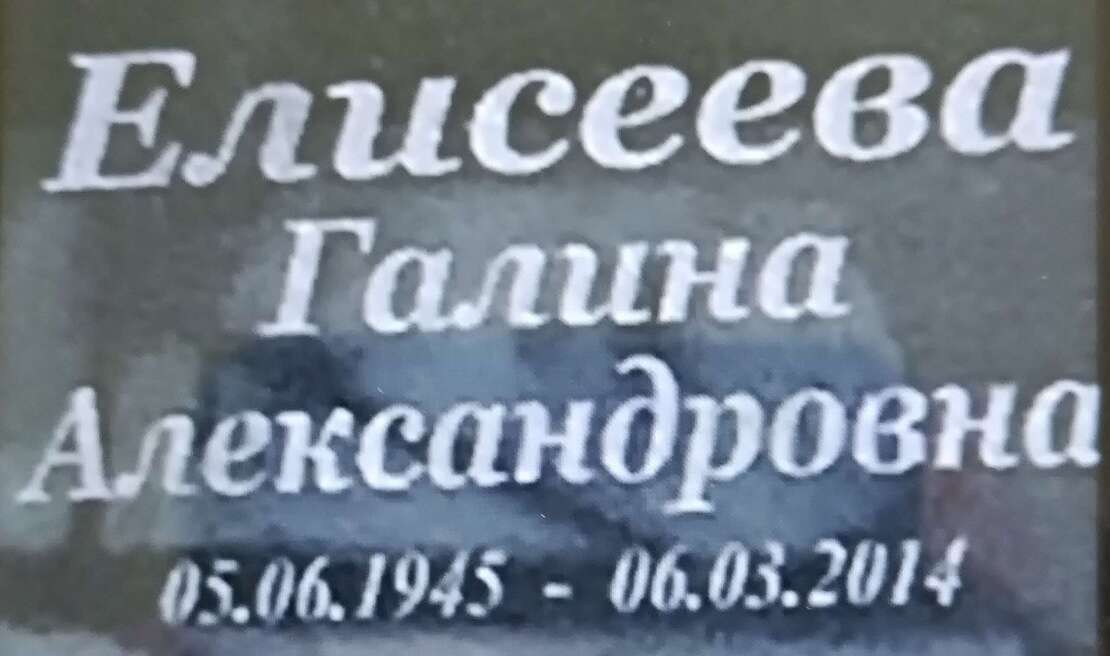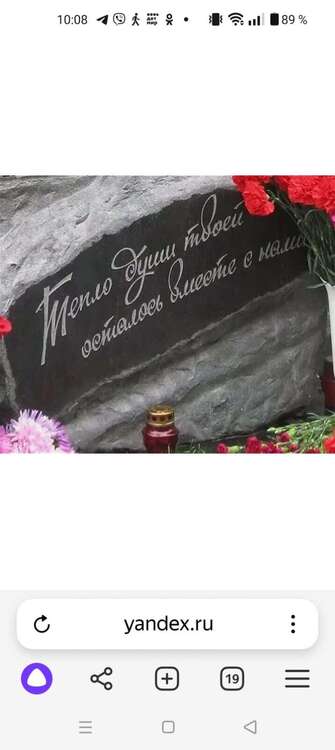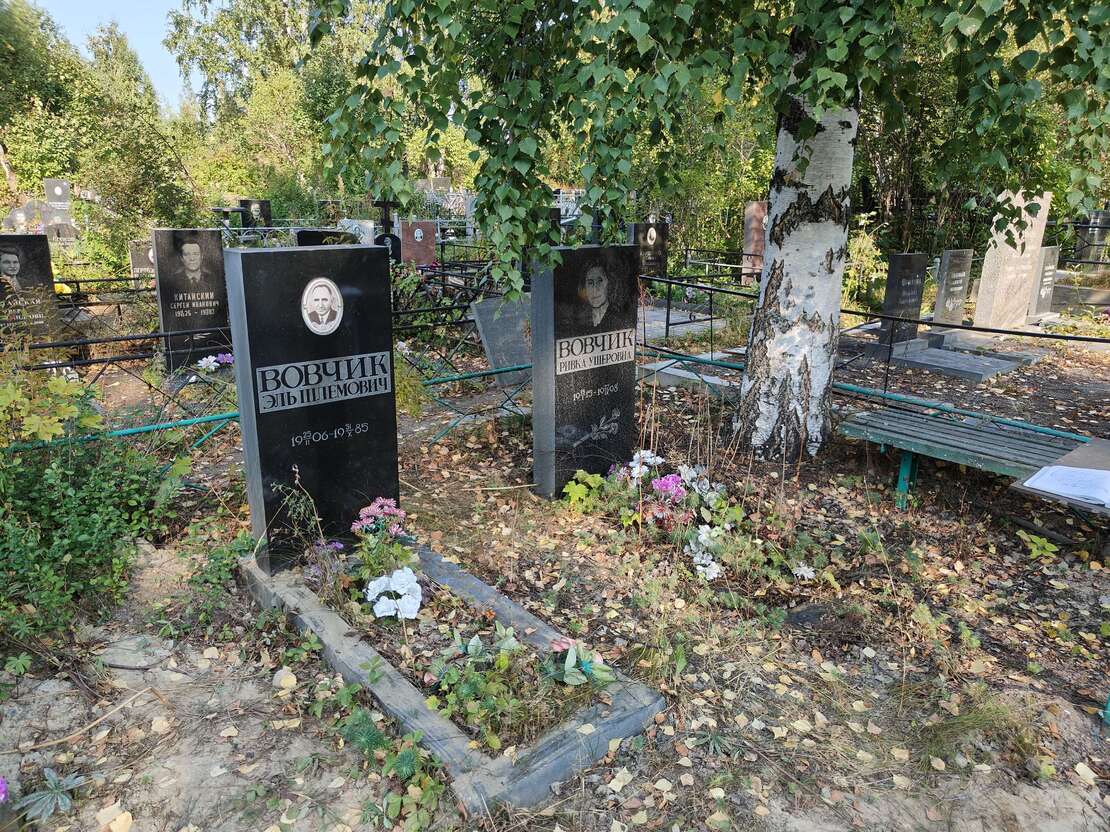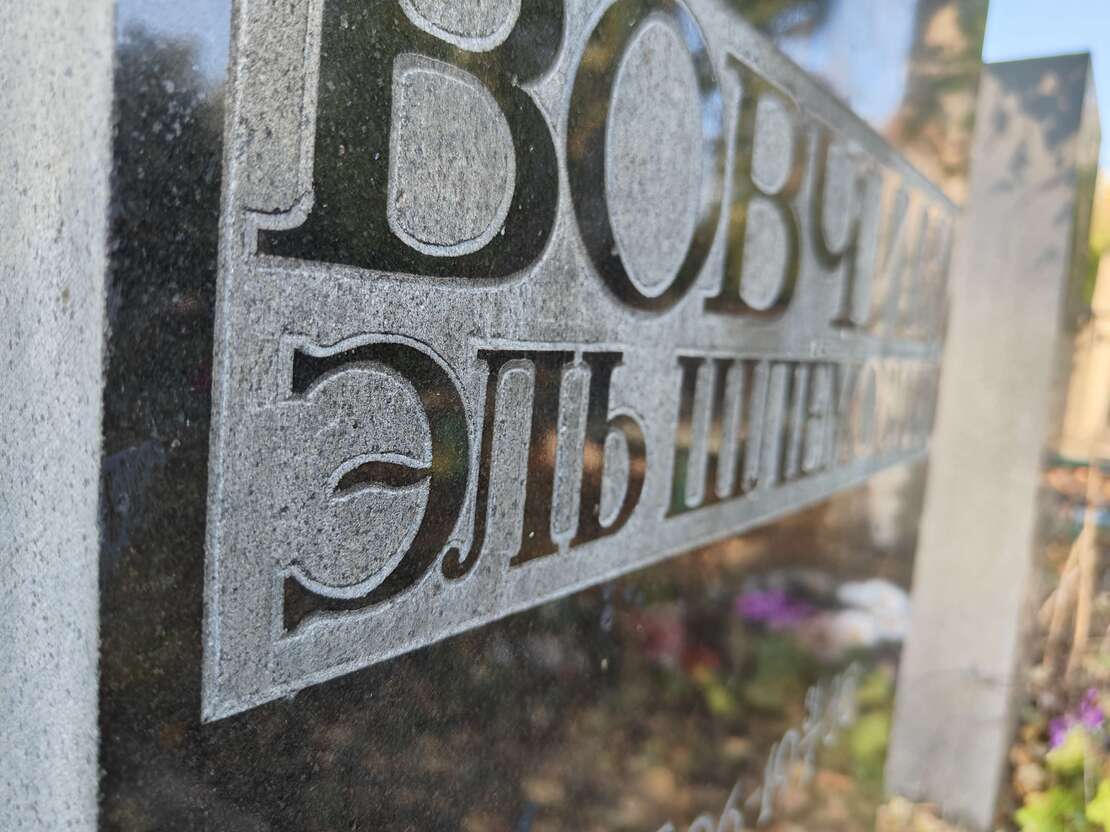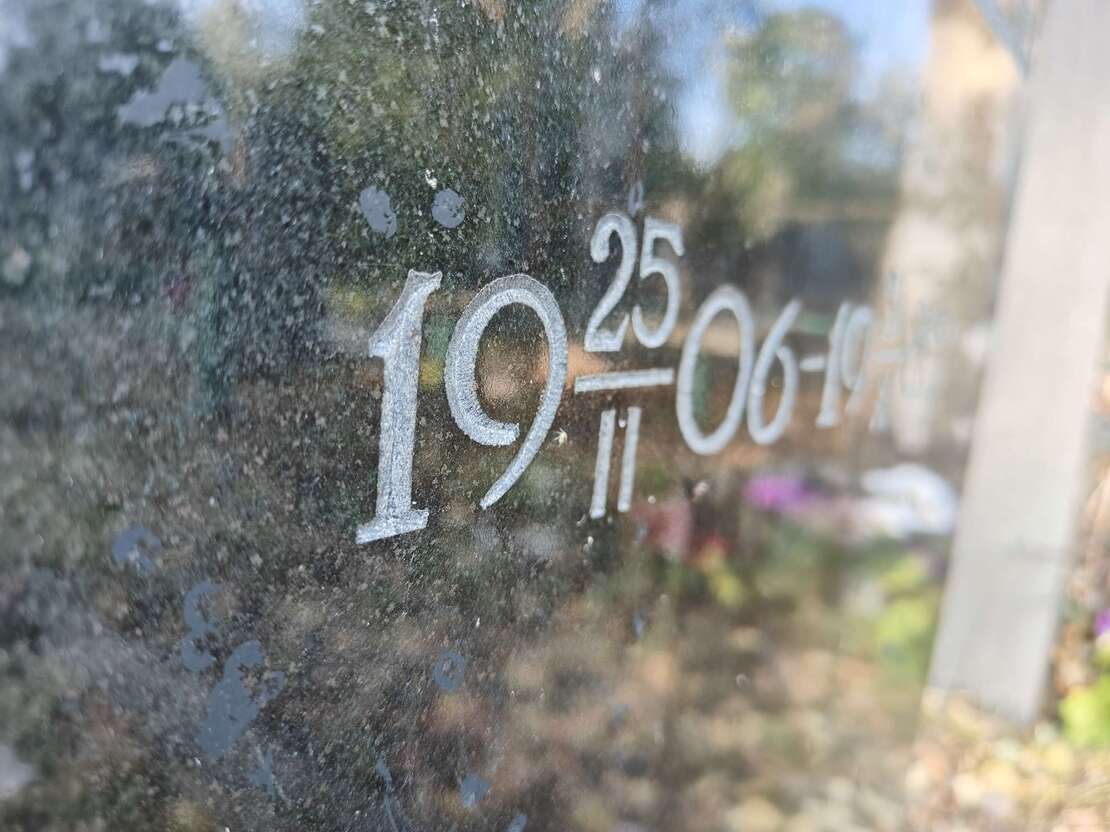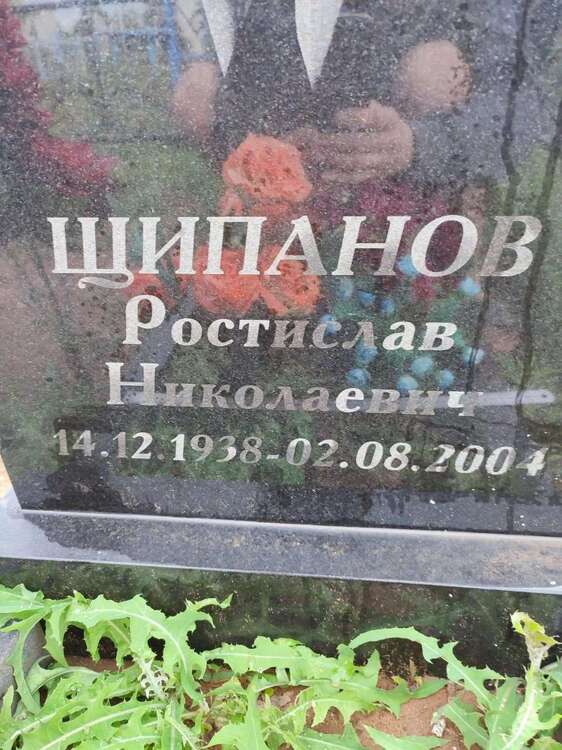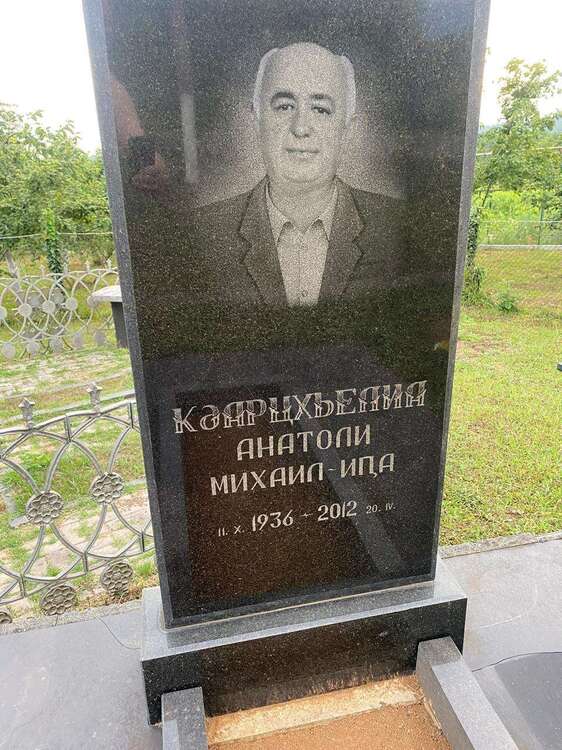
Помогите найти шрифт!
Здравствуйте, помогите пожалуйста найти шрифт, может кто знает
Всех приветствую ! Помогите найти шрифт пожалуйста !
@В.001  Такого шрифта для фотошопа нет в природе. Это ручник - виртуоз.
Помогите пожалуйста найти шрифт :r_help::r_help:
помогите найти шрифт
подскажите на что похоже
- фамилия интересует
@ey19       Constantia italic  Этот посмотри. Только сузить надо буквы.
Подскажите пожалуйста, что за шрифт?
Всем привет. Подскажите кто знает , что за шрифт такой ?
Сборная солянка очередного ручника.....